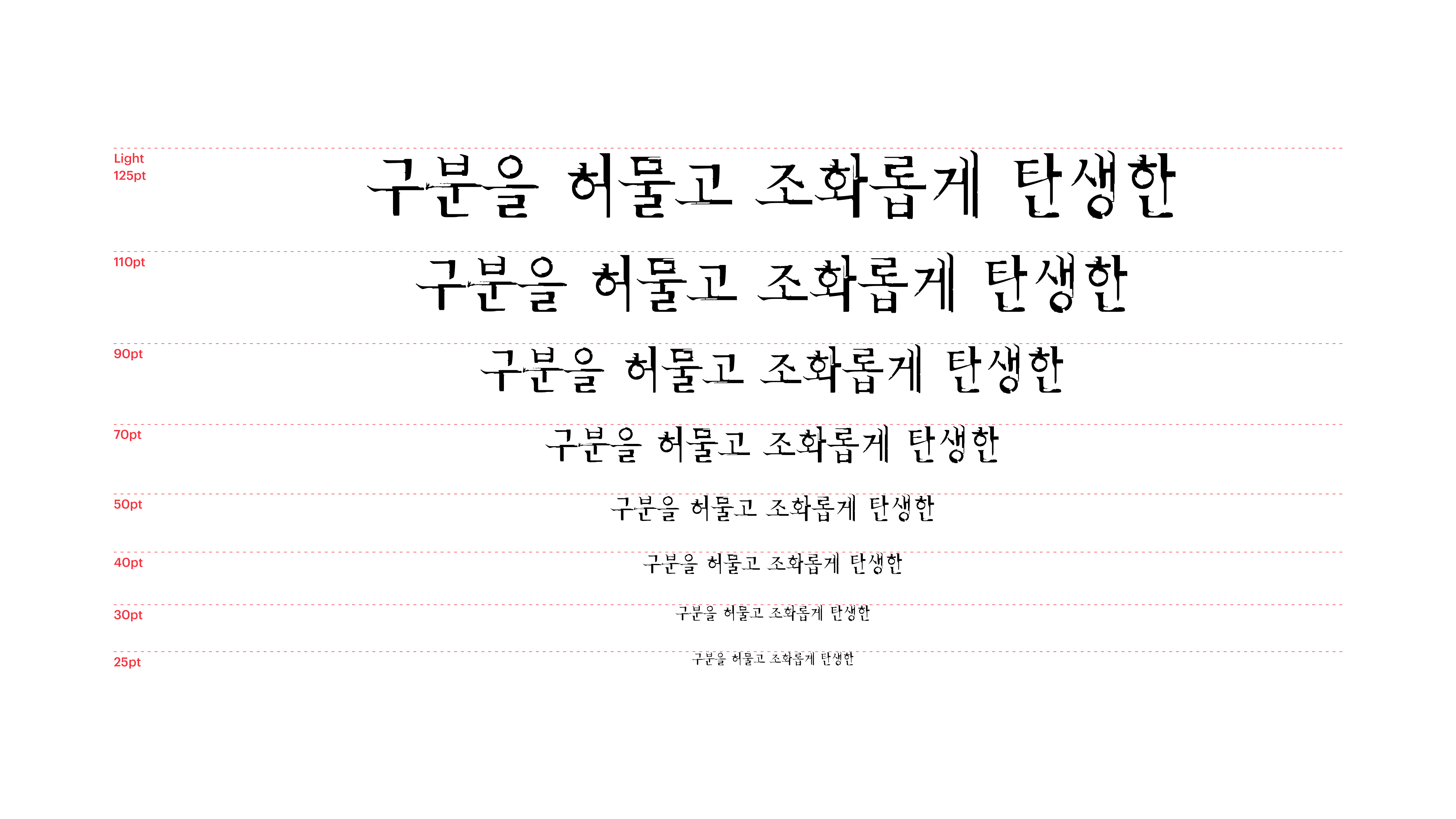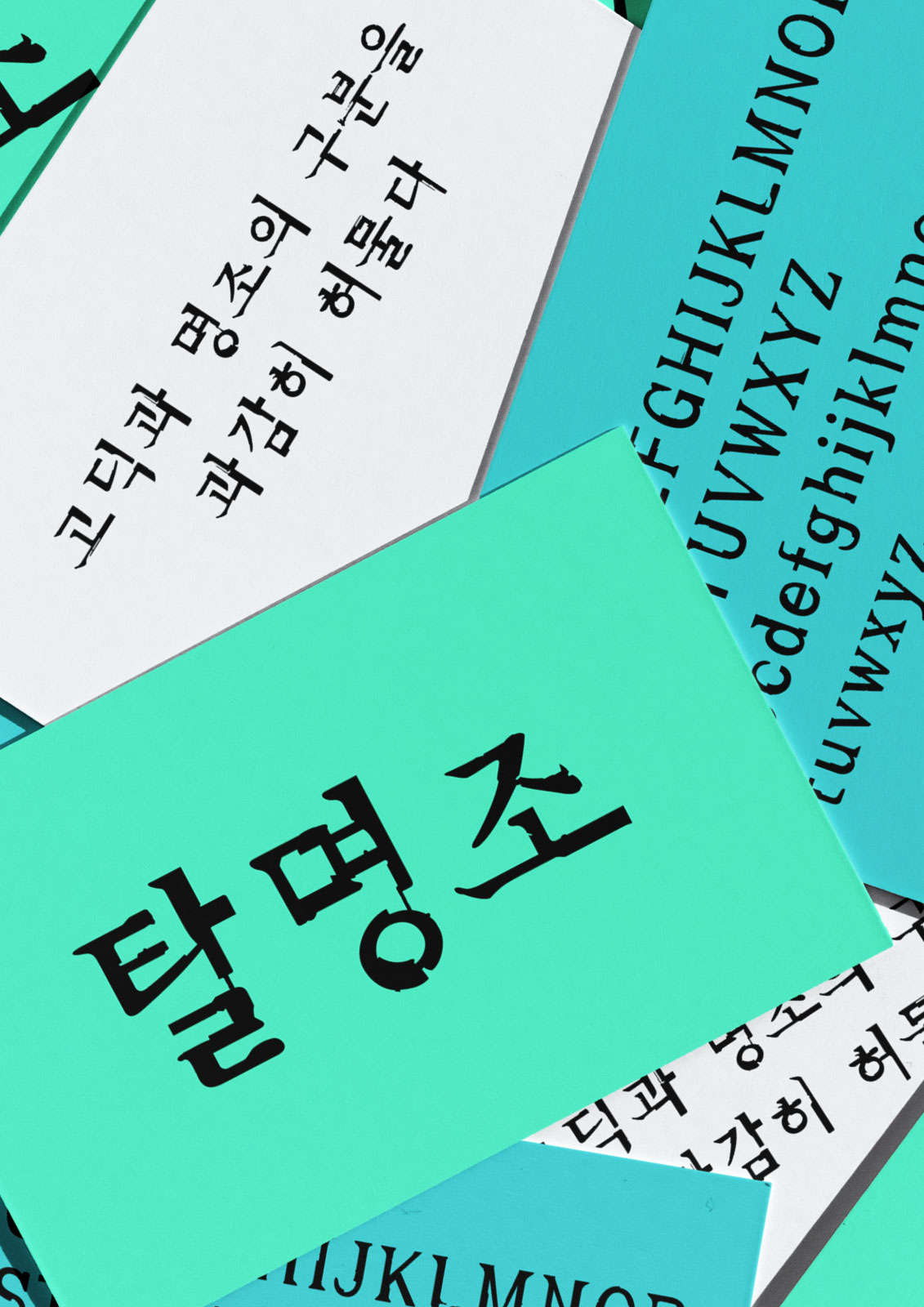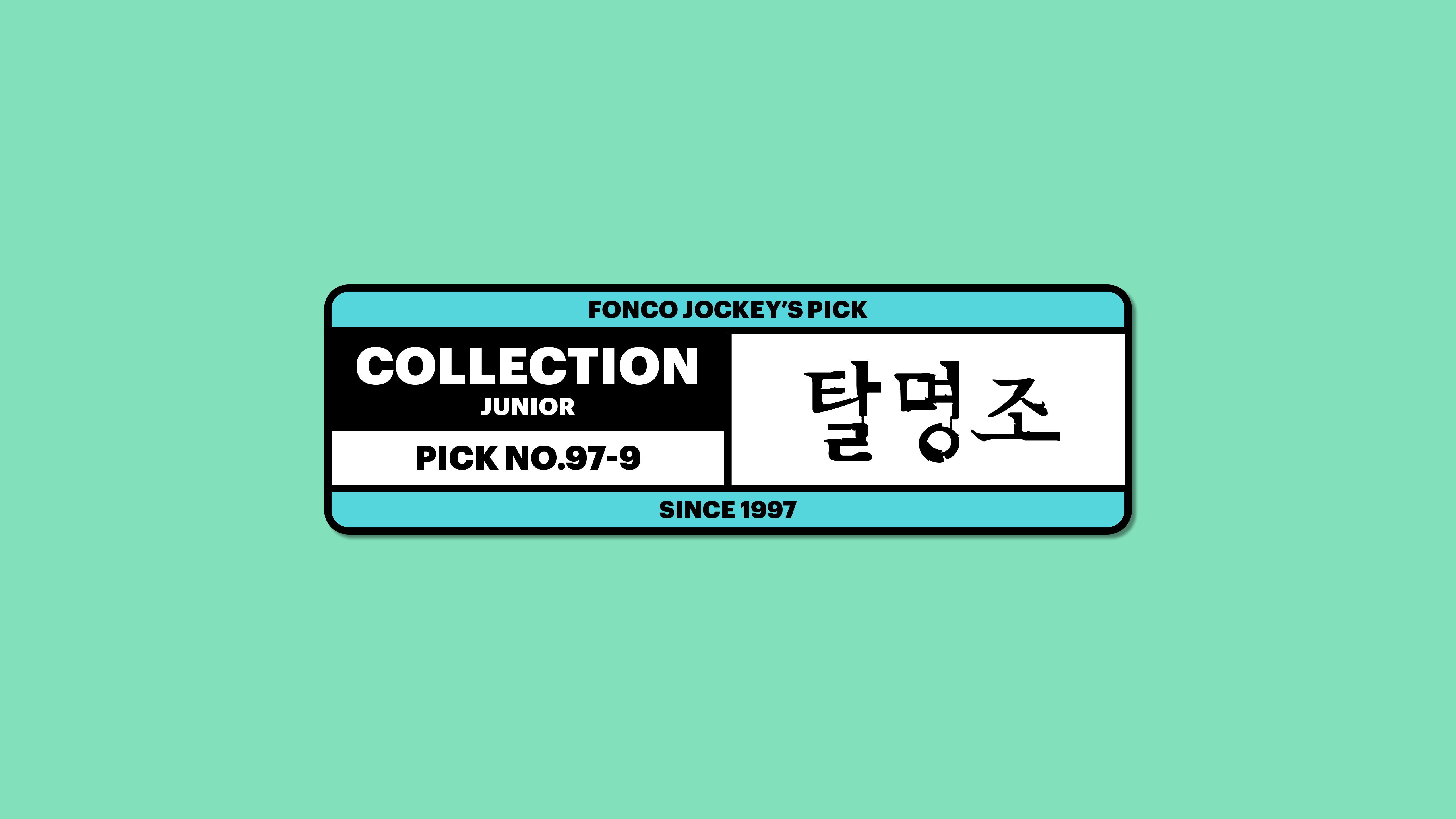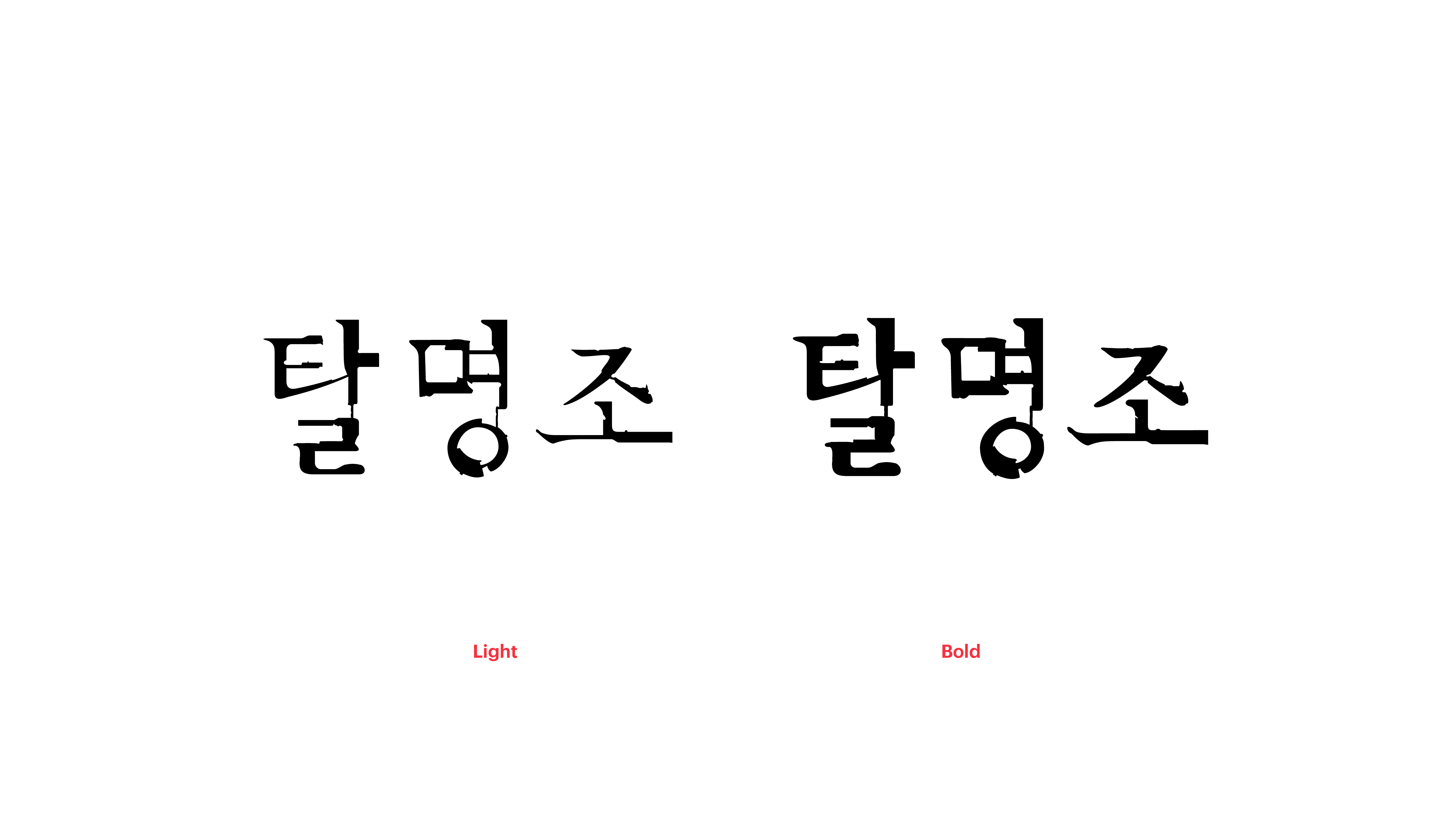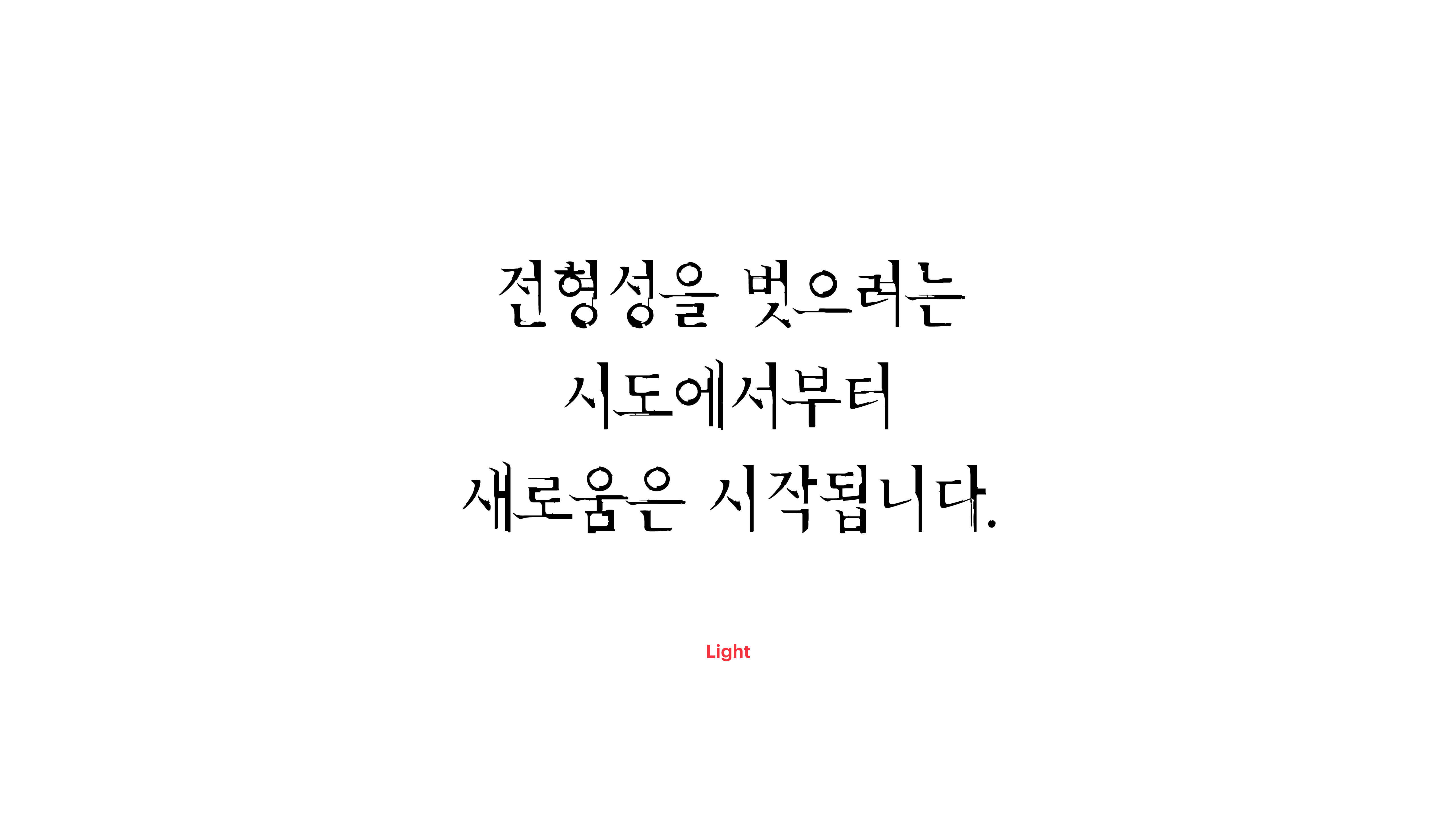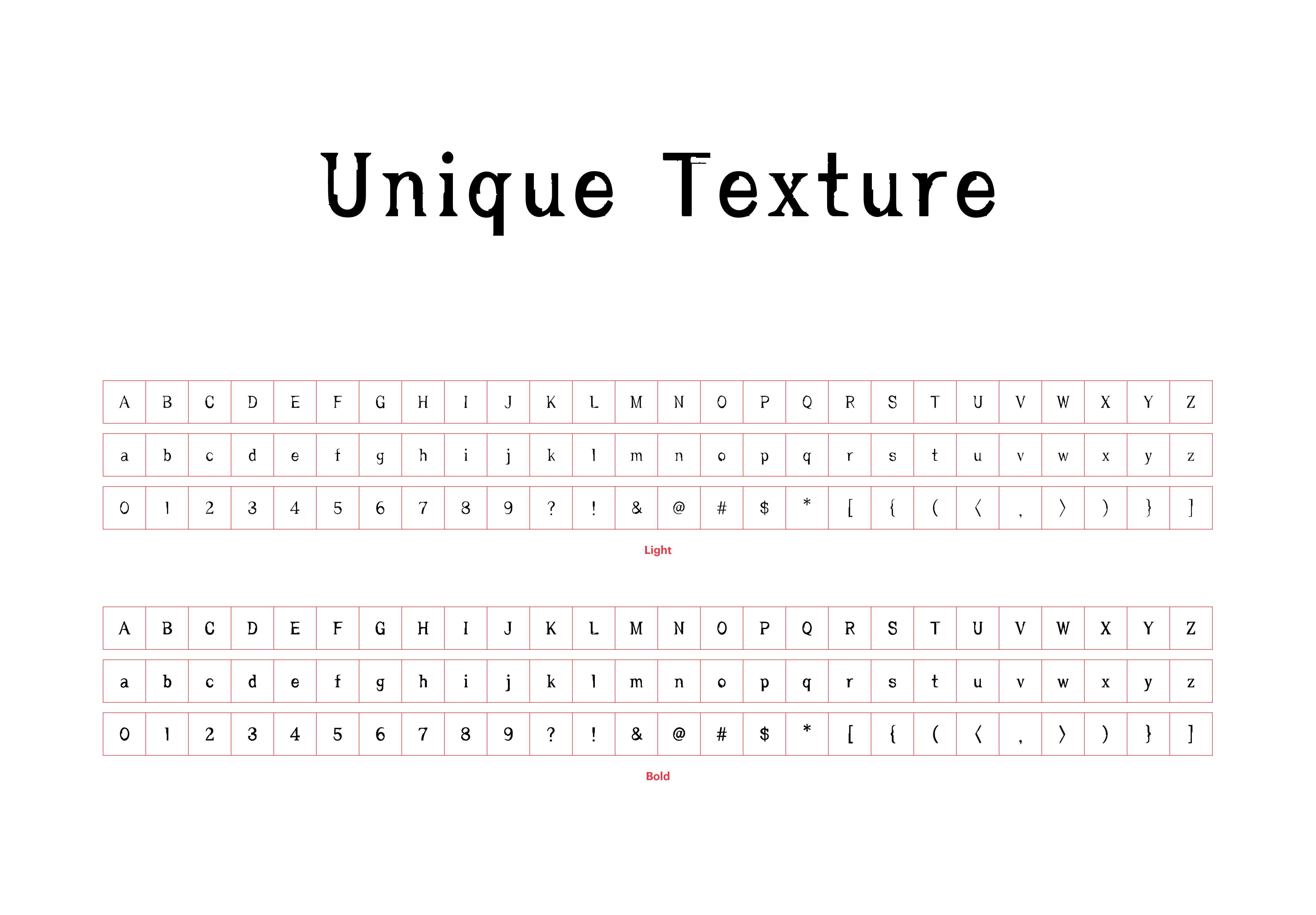
탈명조
Yoon 탈명조
전형성을 벗으려는 시도에서부터 새로움은 시작됩니다. 탈명조는 고딕, 명조의 구분을 과감히 허물고, 둘 사이의 조화를 고민한 새로운 스타일의 폰트이지요. 고딕체를 닮아 깔끔하게 떨어지는 동시에, 명조의 부드러운 돌기로 아름다움을 뽐내는 탈명조. 자연스러운 질감 처리가 두 가지 폰트의 장점을 더욱더 조화롭게 아우릅니다.